폰트를 고르는 스마트한 방법
이 폰트를 왜 골랐어요?
로고 디자인이나 브랜딩 작업을 하다 보면, 종종 본인이 고르거나 제작한 폰트에 대한 설명을 해야 할 필요가 있습니다. 단순히 예뻐서, 심플해서라는 골랐다는 답변은 클라이언트를 설득시키기도 어려울뿐더러, 클라이언트와의 의견 충돌로 이어질 수 있습니다. 또한 다른 사람들에게 공감을 받기도 어렵겠죠.
비교적 역사가 짧은 한글 타이포그래피에 비해, 영문 타이포그래피는 오랜 역사를 바탕으로 그 당시 역사적 배경이나 특수한 목적에 부합하기 위해 끊임없이 개발되고 개량되어왔습니다. 따라서 영문 타이포그래피를 깊이 이해한다면, 본인이 전달하고자 하는 메시지를 보다 효율적으로, 보다 심도 있게 표현할 수 있을 것입니다.
이 글에서는 디스플레이용과 본문에 사용할 영문 폰트를 고르는 방법론과 여러 팁에 대해 소개하려고 합니다.
디스플레이용 폰트 고르기.
텍스트 로고와 디스플레이 용도로 사용되는 폰트를 고를 때 고려해야 할 점에는 크게 두 가지가 있습니다.
1) 브랜드 혹은 서비스에서 의도한 가치와 특징을 함축적으로 담아내기
2) 전달하고자 하는 이미지와 다른 사람들에게 받아들여지는 이미지를 일치시키기
우선, 브랜드의 포지션에 맞춰 그에 해당하는 폰트를 고르기 위해 좌표평면으로 표현해보겠습니다.
Classic vs. Modern (x축)
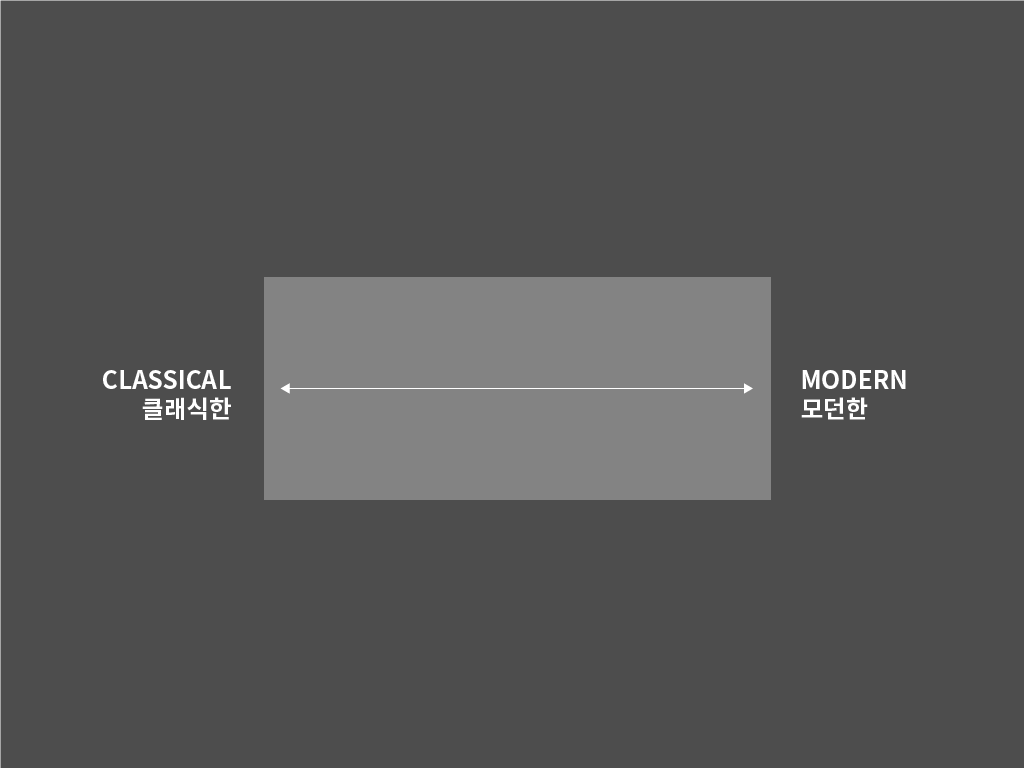
첫 번째 기준이 될 X축은 클래식함 vs. 모던함입니다. 영문 타이포그래피는 세리프(Serif) 폰트와 산세리프(San-serif) 폰트로 분류되는데요, 초기 필기체에 기반에 디자인된 세리프체는 잉크 자국을 그대로 살린 세리프 장식으로 클래식함을 표현하기에 적합하며, 모더니즘과 함께 태어난 산세리프 폰트들은 비교적 모던한 느낌을 줄 수 있습니다. 하지만 이 기준 하나로 폰트를 고르기에는 아직 너무 광범위합니다.
그러니 하나의 축을 더 추가해보죠.
Luxury vs. Friendly (y축)
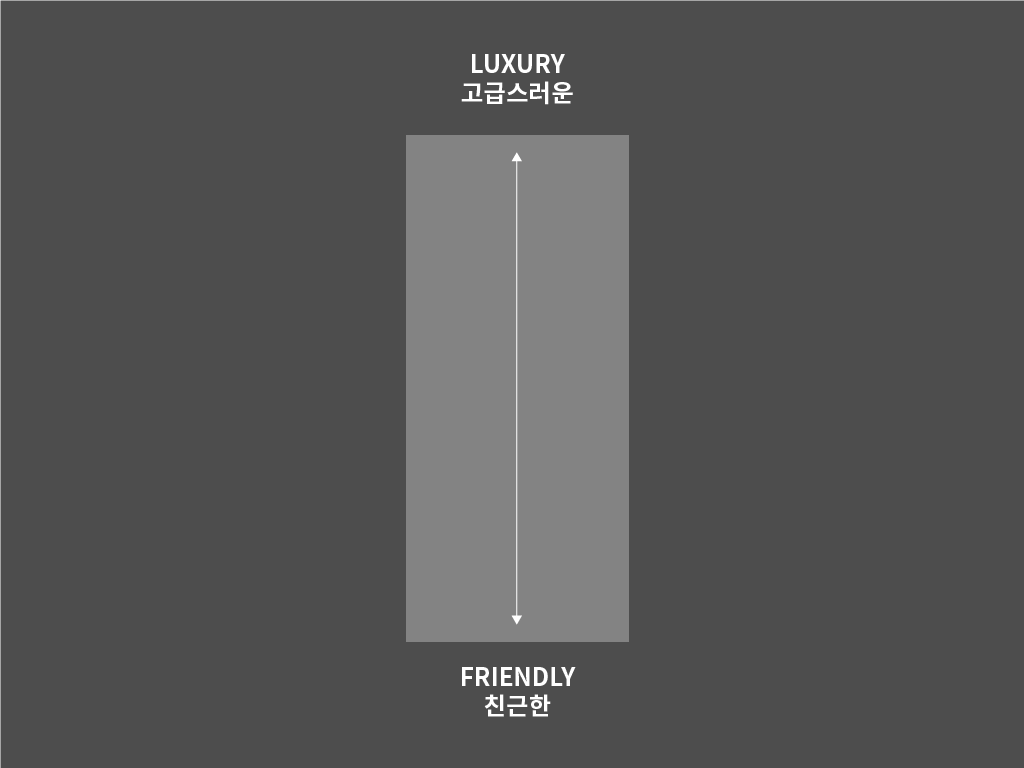
두 번째 기준이 될 Y축은 고급스러움 vs. 친근함입니다. 주로 상류층을 타케팅 하는 럭셔리 브랜드 같은 경우 "아무나 사용할 수 없는" 혹은 "특권층을 위한"라는 인상을 주어야 합니다. 아무나 구입하고 사용할 수 있다면, 럭셔리 브랜드로서의 가치가 하락하기 때문이죠.
하지만 보다 넓은 대상을 타깃으로 하는 브랜드의 경우, "모두나 사용할 수 있는" 또는 "부담 없는"라는 인상을 주어야 합니다. 저가 제품을 판매 하는데 로고가 너무 화려하거나 고급스러우면 소비자가 거부감을 유발할 수 있기 때문이죠. 편의점 브랜드인 CU가 화려한 필기체를 로고로 사용한다고 생각해보시면 이해가 쉬울 것입니다.
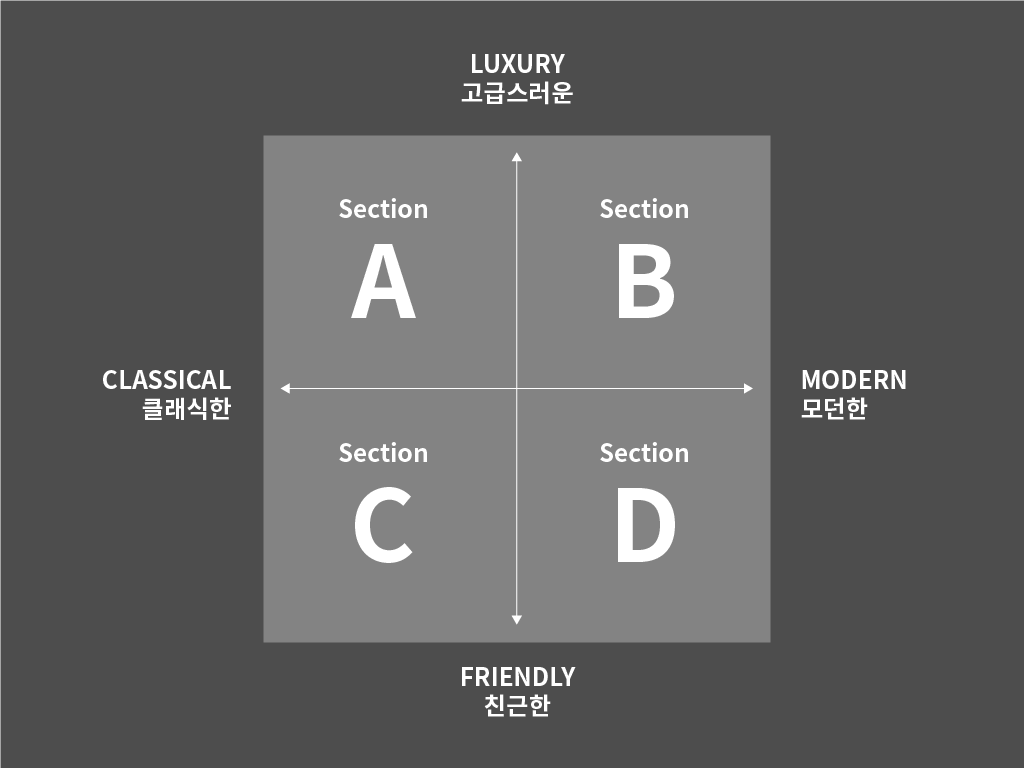
자 그럼 이렇게 XY축들을 기준으로 4개의 면을 나누어 보았습니다. 그렇다면 이 기준선을 토대로 실제 브랜드들은 어떤 서체를 사용하고 있는지 예시를 볼까요?
Section A
클래식한 & 고급스러운
이 카테고리는 보통 역사가 깊은 럭셔리 브랜드들이 많이 해당됩니다. 대표적으로 럭셔리 액세서리와 시계를 제조하는 프랑스 브랜드, Cartier를 예시로 들 수 있습니다. Cartier는 세리프 폰트 중에서도 디돈(Didone) 스타일의 폰트를 활용하여 클래식하면서도 고급스러운 인상을 줍니다. (18세기에 등장한 디돈 세리프는 획의 두께 대비가 크고, 공 형태나 뭉툭한 세리프가 특징으로 Cartier 외에도 VOGUE, ELLE와 같은 여러 브랜드에 사용되었습니다.)
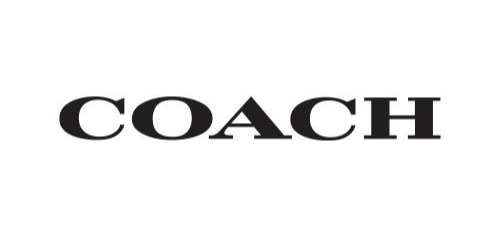
어떤 폰트를 사용하나요?
금속 세공 같은 섬세한 작업을 요구하는 브랜드들은 얇은 세리프 폰트를 선호하고, 가죽 제품같이 무게감 있는 작업을 주로 하는 같은 브랜드(ex: Coach)들은 두꺼운 세리프 폰트를 활용하는 것을 볼 수 있습니다.
Section B
모던한 & 고급스러운
이 카테고리는 럭셔리 브랜드 중에서 비교적 역사가 짧거나 노후화된 이미지를 탈피하고자 하는 브랜드들이 포함됩니다. 유명 의류 브랜드인 Calvin Klein을 예시로 들어볼까요? Calvin Klein의 로고는 얇은 두께의 산세리프 서체를 사용하여 미려하면서도 세련된 인상을 줍니다. 또한 전부 대문자임에도 불구하고 좁은 자간과 글자의 너비가 좁은 폰트의 활용으로 로고가 느슨해 보이는 걸 방지합니다.
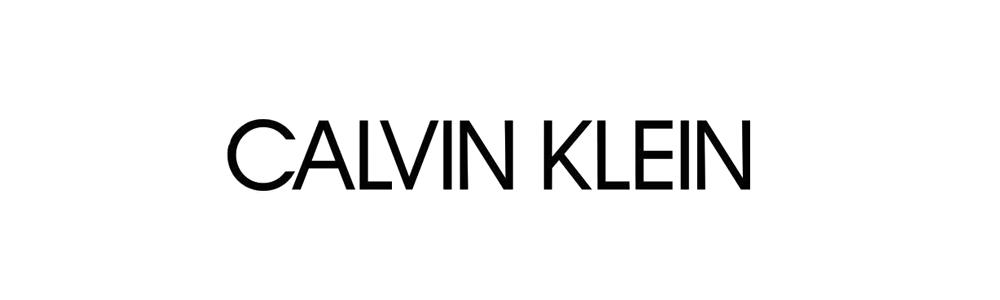
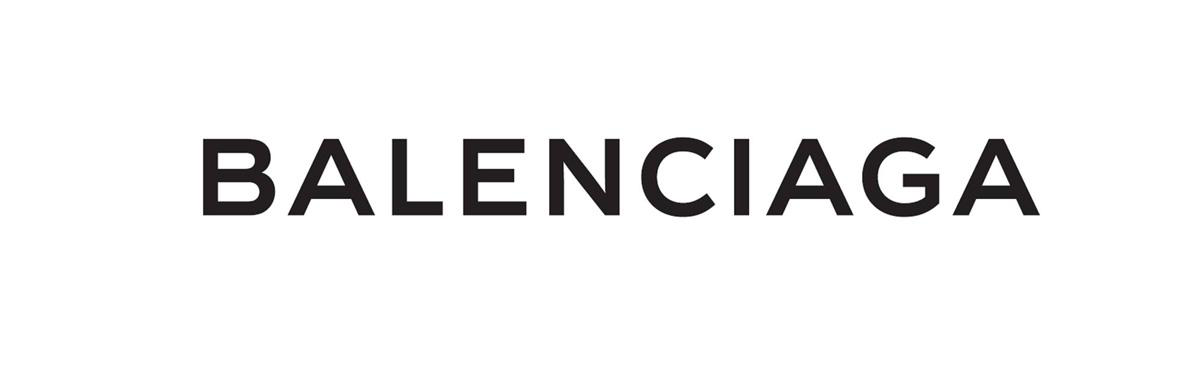
어떤 폰트를 사용하나요?
주로 글자 자체의 특색이 적고, 얇은 두께의 산세리프 폰트를 사용합니다. 특징이 너무 눈에 띄는 폰트는 자칫하면 가벼워 보일 수 있고, 너무 두꺼운 폰트는 둔탁한 인상을 줄 수 있기 때문이죠.
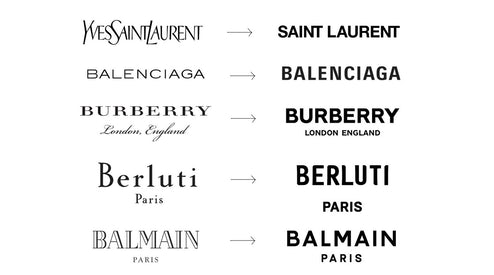
최근 여러 클래식 브랜드들이 노후화된 이미지를 탈피하고 모던한 인상을 주기 위해 세리프 폰트에서 산세리프 있는데요, 모바일과 웹 등에서의 환경에서 로고의 시안성과 접근성을 높이기 위한 이유도 있습니다.
Section C
클래식한 & 친근한
아마 이 카테고리는 나머지 세 개에 비해 가장 적은 포지셔닝일 것입니다. 최근 수많은 브랜드들이 여러 이유로 산세리프 폰트를 활용한 로고타입으로 리브랜딩을 진행하고 있기 때문이죠. 주로 신뢰성을 바탕으로 여러 고객층을 타케팅 하는 식료품 혹은 코스메틱 브랜드들이 이에 포함됩니다.
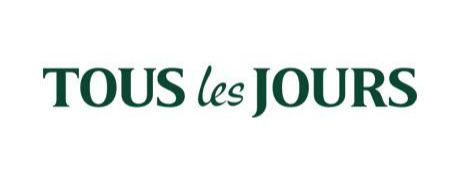
어떤 폰트를 사용하나요?
너무 권위적인 느낌이 들지 않는 세리프 폰트나 비교적 자유로운 캘리그래피 폰트를 많이 사용합니다.
Section D
모던한 & 친근한
아마 이 카테고리에 해당하는 브랜드들을 가장 많이 보실 수 있을 것입니다. 남녀노소 가리지 않고, 모든 계층의 사람들을 타기팅 하는 브랜드들이 모두 포함되기 때문입니다. 대표적인 예시로 세계 최대 검색 엔진이자 IT 기업인 Google을 예시를 들 수 있는데요, 기하학적 도형들에 기반한 폰트는 모던하면서도 친근한 인상을 줍니다.
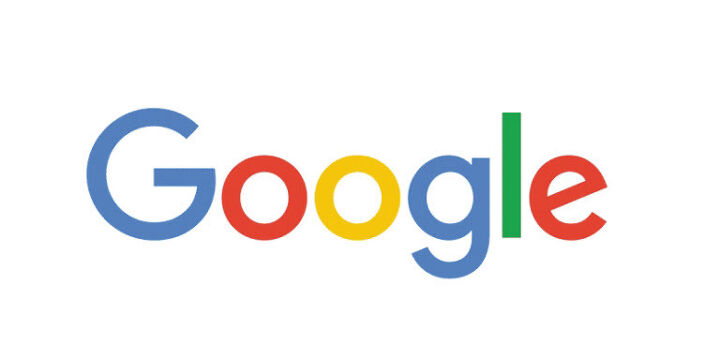
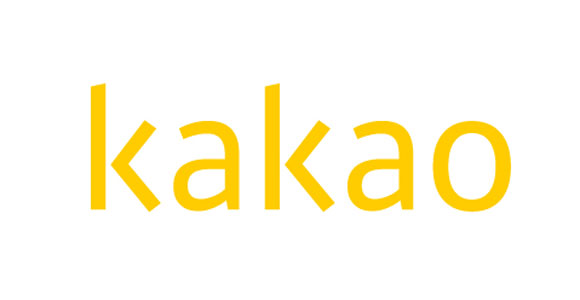
어떤 폰트를 사용하나요?
스타트업이나 IT기업에서는 혁신적인 인상을 주기 위해 산세리프 서체 중에서도 기하학적 도형에 기반한 Geometric 폰트 혹은 브랜드의 특징을 담은 커스텀 산세리프 폰트를 많이 사용합니다.
너무 중립적이거나 딱딱한 그로테스크(Grotesque) 산세리프 폰트들은 브랜드의 개성을 죽일 수도 있으니 이 점 유의해주세요.
본문용 폰트 고르기.
우리는 앞서 디스플레이용 폰트를 고르는 방법에 대해 알아봤습니다.
그렇다면 본문용 폰트를 고를 때 고려해야 점들은 무엇이 있을까요?
바로 가독성과 판독성입니다.
1. 가독성 Readability - 얼마나 글자를 읽기 쉬운가?
2. 판독성 Legibility - 얼마나 글자를 인지하기 쉬운가?
가독성은 텍스트가 얼마나 쉽게 읽히는 지를 정하는 척도입니다. 가독성이 높은 글은 본문(body text)에서 정보 전달력을 높이고 글을 읽는 데 있어 집중을 도와줍니다. 반면, 각각의 글자를 구별하고 인지하기 쉬운가를 판단하는 판독성은 먼 거리에서도 단어들을 인식할 수 있게 도와주고, 비슷한 글자의 혼동을 방지합니다.
어떤 폰트가 본문(Body Text)에 적합한가?
오랜 시간 동안 그래픽 디자인에서는 편집 디자인용 폰트 = 세리프 폰트라는 암묵적인 룰이 존재하고 있었습니다. 이는 초창기 산세리프 폰트가 본문용보다는 간판이나 사이니지의 용도로 위해 디자인되었기 때문입니다. 하지만 가독성을 높인 산세리프 폰트들이 개발됨에 따라 많은 산세리프 서체들을 편집 디자인에서 찾아볼 수 있습니다.
| 가독성 & 판독성이 좋은 폰트를 고르는 팁
[Tip 1] 간격 조정이 잘 되어있는 폰트를 찾아라.
가독성이 좋은 폰트를 찾는 첫걸음은 Spacing과 Kerning이 잘 되어있는 폰트를 찾는 것입니다. 글자 간격이 잘 조정되어 있지 않는 폰트를 사용하게 된다면 가독성에 큰 영향을 끼치게 되며, 이를 수정하는 데에도 상당한 시간이 소비됩니다. 처음부터 완성도 있는 폰트를 사용하는 것이 시간을 아끼는 방법입니다.
[Tip 2] x-height가 높은 폰트를 찾아라.
x-height는 소문자 x를 기준으로 하는 기준선입니다. 크기가 작은 텍스트일 경우 이 x-height가 높아질수록 글자의 갇힌 공간(counter)이 넓어지게 되어 글자를 인식하는 속도가 빨라진다는 연구 결과가 있습니다.
[Tip 3] 획이 대비가 적절한 폰트를 찾아라.
왼쪽과 오른쪽 중 어느 쪽이 읽기 편한가요? Didot은 Didone Serif에 속하는 폰트로 글자 획의 두께 대비가 매우 큰 서체입니다. 따라서 글자가 작아질수록 얇은 획은 거의 보이지 않게 되고, 이로 인해 가독성이 크게 저하되는 것을 볼 수 있습니다.